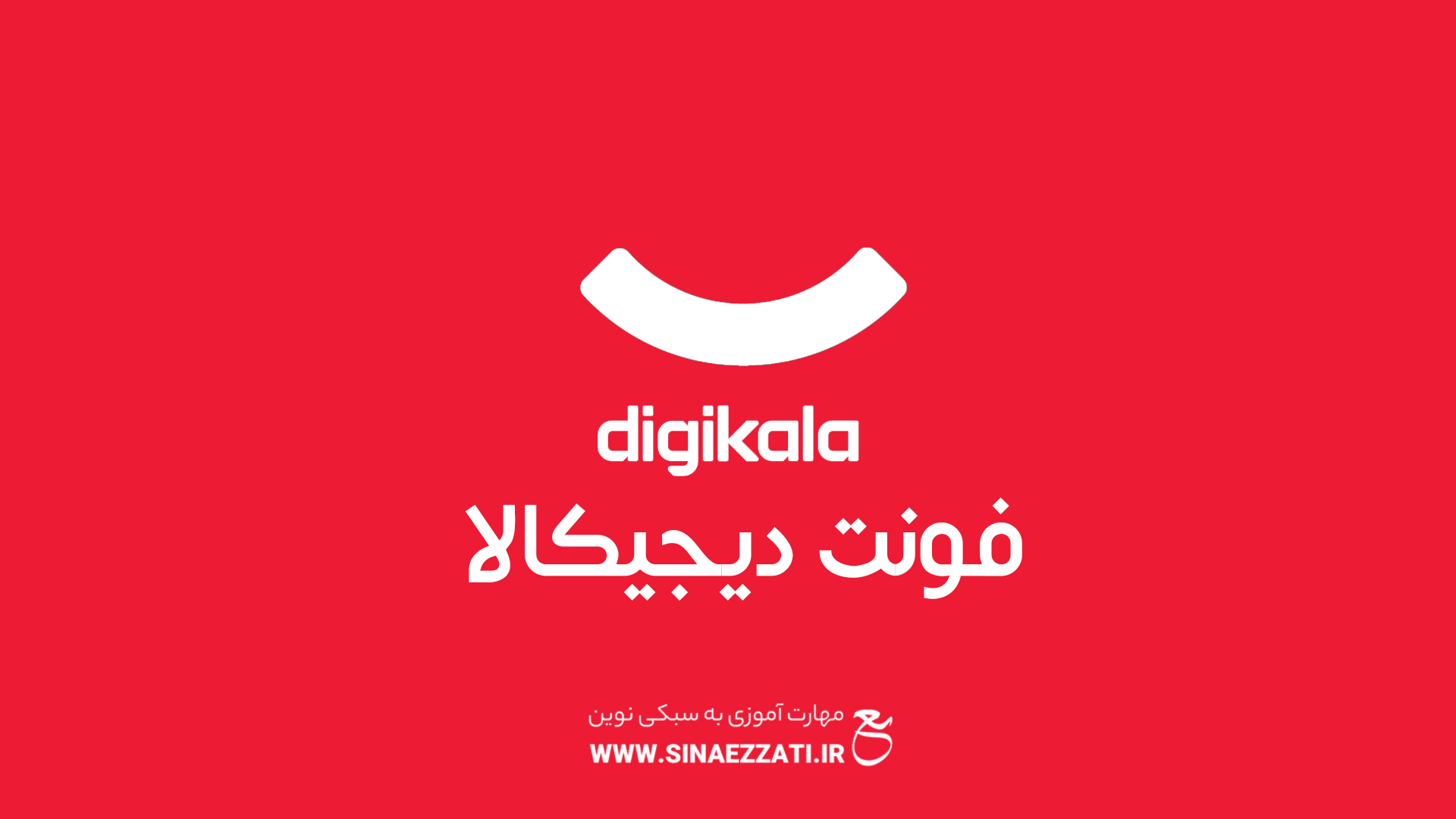
فونت فارسی دیجیکالا با طراحی منحصر به فرد و حروفی پویا، به شما این امکان را میدهد که توجه هر بینندهای را به خود جلب کنید. این فونت مناسب برای وبسایت، پست ، بنر، و … همچنین میتوانید در نرمافزارهایی مانند فتوشاپ، ایلاستریتور و کورل دراو از آن استفاده کنید
نمونه ای از فونت